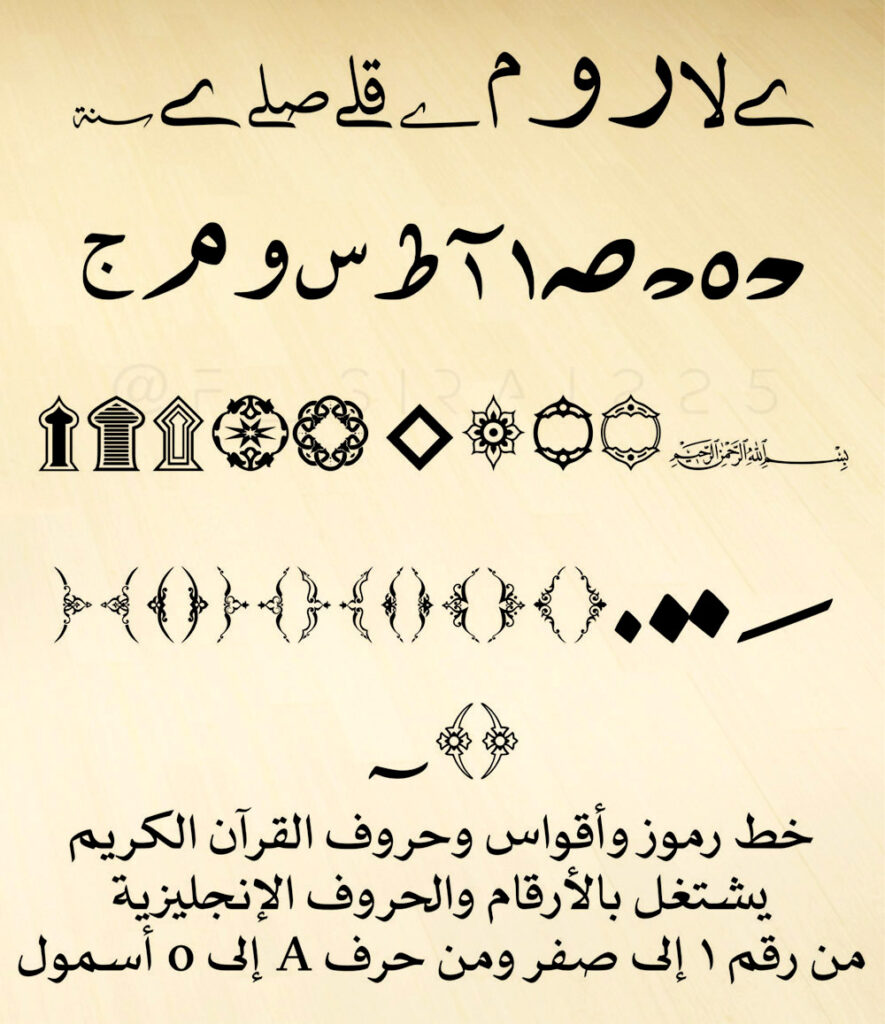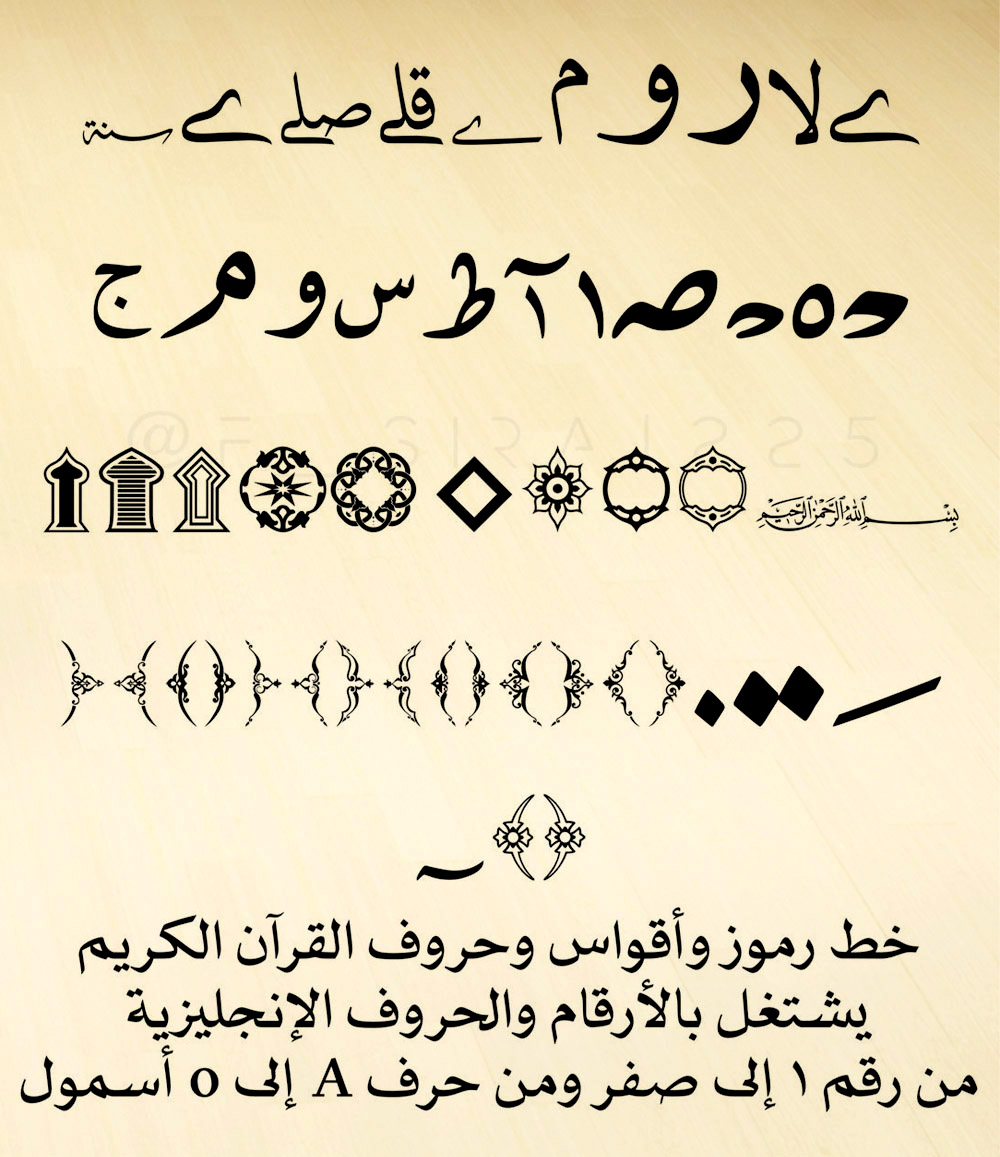
خط تشكيلات رموز وأقواس وحروف القرآن الكريم
خط تشكيلات رموز وأقواس وحروف القرآن الكريم .. خط جميل يحتوي على جميع الرموز الخاصة بالقرآن الكريم من أقواس وحروف وتشكيلات وغير ذلك، يمكن الاستفادة من الخط في الأعمال الفنية واللوحات الكبيرة والتصاميم الإسلامية، كما يعمل الخط بالأرقام الإنجليزية من (1) إلى (0)، وبالحروف الإنجليزية الصغيرة من (a) إلى (o)، الخط من أعمال : فوزية سراج، وهو متاح للتحميل المجاني الآن.